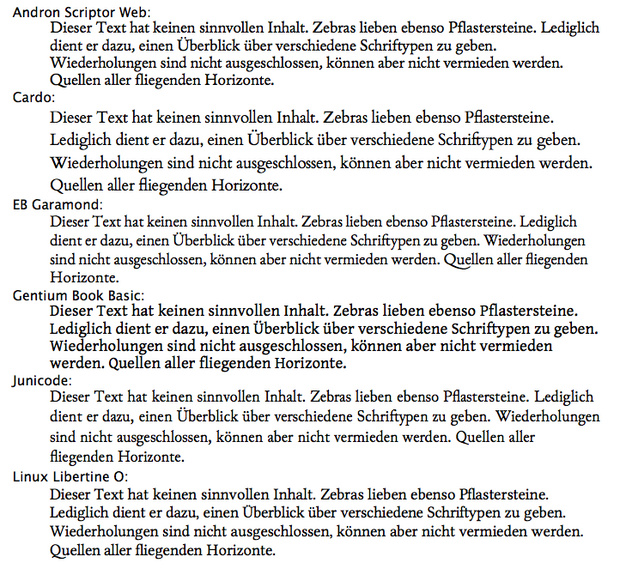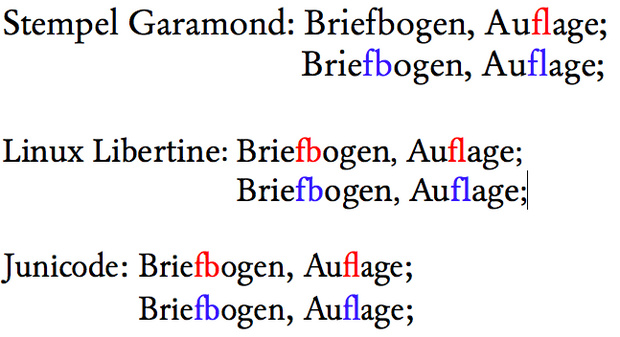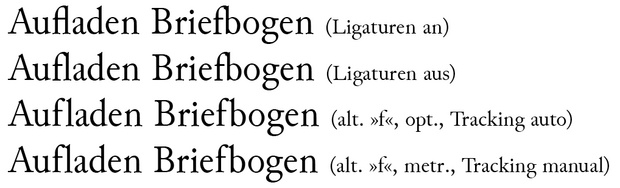
Veröff. wiss. Arb.: freie Serife gesucht. Tipps?
Ich habe die Gelegenheit erhalten, in dem Universitätsverlag meiner Alma Mater meine Diplomarbeit zu veröffentlichen. Dabei bleibt einem der Satz selbst überlassen. Bedingung ist natürlich, dass mit der verwendeten Schrift keine Rechte Dritter verletzt werden. Außerdem benötige ich eine Schrift, deren Zeichensatz DIN 31635-konforme (Arabisch->Lateinisch) Umschrift ermöglicht (also so Sachen wie: ā, ḥ, ǧ etc.).
Eine Vorliebe habe ich für klassische "garamondesque" (Favorit: Stempel Garamond LT) bzw. etwas rauere "bembohafte" (Favorit: Bembo Book MT Pro) Schriften; muss aber nicht zwingend sein.
Meine Recherche hat mich bis jetzt zu folgenden Schriften geführt:
a) Junicode (Manchmal wirkt sie auf mich etwas schmal und hoch. Aber insgesamt bei mir bis jetzt an erster Stelle - schöner Kursivschnitt, leider mag ich das kleine "a" nicht so ganz und auch das große "T" [ok, ich glaube ich werde da langsam zu pingelig ;) ])
b) EB Garamond (Sehr schön. Scheint aber leider noch etwas "beta" zu sein - vor allem der Kursivschnitt.)
c) Cardo (Bembovariation. Kommt mir aber etwas gar grob vor.)
d) Gentium (Wahrscheinlich der umfangreichste Zeichensatz. Aber irgendwas stört mich an ihr... ein wenig "klobig" bzw. "unelegant". Es gäbe allerdings eine leicht fettere Book-Variante)
e) Linux Libertine (Auch alles dabei was man braucht. Testausdrucke auch sehr leserlich und aufgeräumt, aber fast ein bisschen zu "Textbook"-haft , d. h. sehr neutral [vor allem der Kursivschnitt])
Die Reihung ist in gewisser Weise auch nach Präferenz gestaffelt.
Ich habe darüber hinaus auch über die "Minion Pro" nachgedacht, da sie bekanntermaßen mit dem Acrobat Reader installiert wird und als eine ausgezeichnete Buchschrift gilt. Allerdings habe ich da nichts genaues zu den Linzenzaspekten finden können; manche sage dies, andere jenes.
Meine Fragen betreffen vor allem zwei Punkte:
a) Was haltet ihr vorn den Schriften allgemein; kennt jemand was "besseres"?
b) Welche Schrift würdet ihr empfehlen im Hinblick auf die Buchveröffentlichung? Ist eine der Schriften zu feinlinig für Langtexte? Oder wie sieht es mit den "Höhenverhältnissen" (Klein- zu Großbuchstaben) aus?
mein tipp: investiere ne mark fuffzich in die andron. der font ist nicht billig, aber hervorragend geeignet für deine zwecke und sehr ausgewogen. das solltest du dir wert sein ;)
Sind die anderen denn so schlecht?
Sehr hübsch die falschen Kapitälchen im Kopf der Website inklusive des normalen ß ...
Gibt es eigentlich schon einen Browser, wo echte Kapitälchen wie vorgesehen über font-variant: small-caps funktionieren, und nicht nur über den Umweg von (-x-)font-feature-settings? Ich habe gerade das Forum so umgestellt, dass es in den Kapitälchen der Linux Libertine – wohl auch ein empfehlenswerter Font – angezeigt wird, und zwar per -moz-font-feature-settings: "smcp=1", aber das ist halt nur ein Umweg, sieht aber um Welten besser aus als font-variant!
Ist nicht eher font-variant die "veraltete" Methode, um sowas zu aktivieren?
Im Grunde würde man da eigentlich für jede Schrift-Spezialität einen eigenen Befehl brauchen, der letzlich ohnehin nur ins passende OT-Feature übersetzt, statt über font-feature-settings direkt auf die in der Schrift angebotenen Features zugreifen zu können.
Brill hab ich auch schon entdeckt, danke. Ich kann mich aber nicht so ganz für sie erwärmen.
Hat jemand eine Meinung zur Junicode? Was haltet ihr von der?
Die fällt etwas kleiner aus, aber ist grundsätzlich angenehm zu lesen.
Ich könnte mich aber auch für die Libertine erwärmen, weil hier die e-Punze etwas offener ist. Hat die noch ein »dezenteres« Q als Alternative?
Hast Du Dir eigentlich mal die Vollkorn angesehen?
Zum Teil finde ich die Buchstaben der Junicode etwas unsauber (beispielsweise das kleine u). Ein Problem ist außerdem der große f-Bogen; damit ist die Schrift fürs Deutsche nur mit Abstrichen zu gebrauchen: Entweder Du nimmst in Kauf, daß das f folgende Buchstaben mit Oberlängen überlappt, oder Du fügst einen möglicherweise störenden Abstand ein. Unverständlicherweise enthält die Schrift zwar ein schmaleres alternatives f, das jedoch ebenfalls überlappt. Eine bessere, ausreichend ausgebaute, kostenlose Schrift in ähnlichem Stil wirst Du aber kaum finden, und insgesamt sieht sie schon brauchbar aus. Verwende sie deshalb, wenn sie Dir gefällt.
Die Andron ist übrigens in einer eingeschränkten Fassung kostenlos auf http://www.mufi.info/fonts/ erhältlich. Die Kursive müßtest Du allerdings dazukaufen, und das Problem mit dem überlappenden f-Bogen hat sie auch.
Naja, wie auch immer, mir gefällt die Linux Libertine und Andron Scriptor Web am Besten, auch wenn zweitere im Sreenshot da wohl etwas unvorteilhaft eng gesetzt wurde.
Cardo ist wie einer der andere C-Fonts eigentlich nur ein TNR-Klon, kann sie schon unterscheiden, sehe aber nur marginale Differenzen.
Gentium geht gar nicht, finde ich. Ich finde sie "kindlich" und kann sie nicht gut lesen, bin bei 10 Testausdrucken mit je 2 Seiten vor einiger Zeit (immer mit verschiedenen Zeilenabständen) gar nicht damit warm geworden.